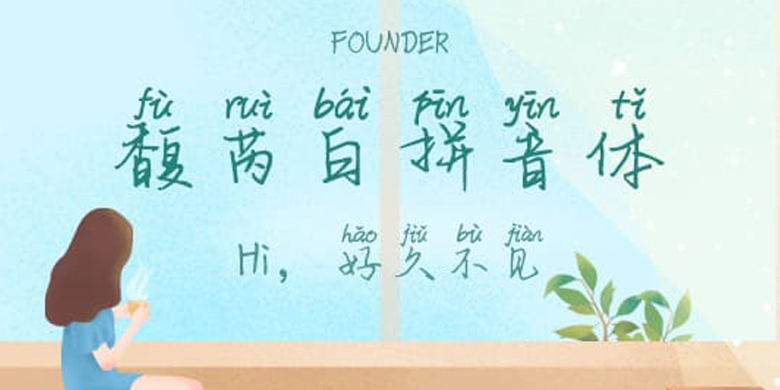
方正手迹-馥芮白拼音体
字体品牌: 方正手迹 设计师:冯子研 字体分类:常规书写·硬笔 字体属性:精品字 字符集:大陆简体(GB2312-80) 发布时间: 2020
这款拼音体用笔飘逸灵动,结字秀美洒脱。结字与行笔都有传统书法的影子,凸显了作者的传统书法的功力。适用于文艺类的书刊、品牌广告和产品包装设计,以及社交网络的个性化用字。